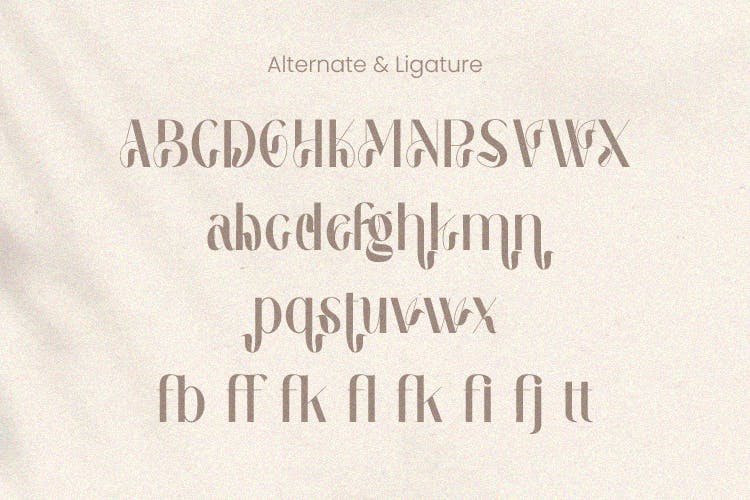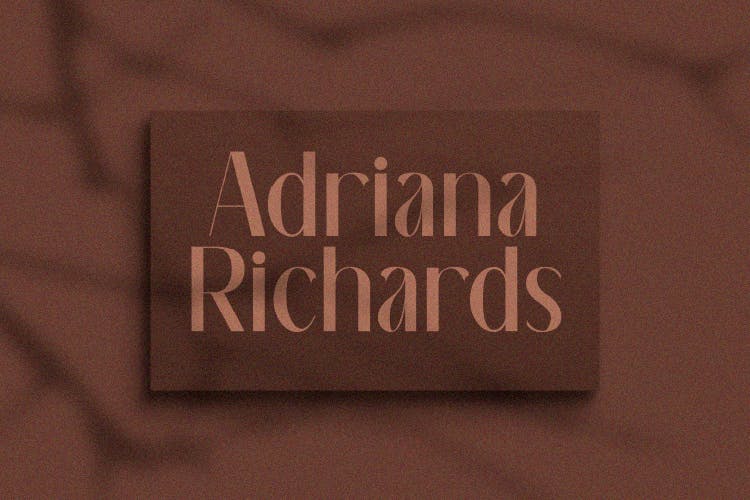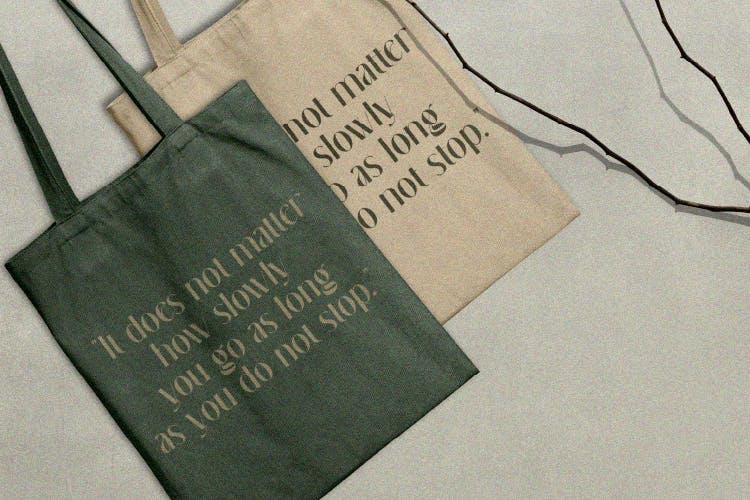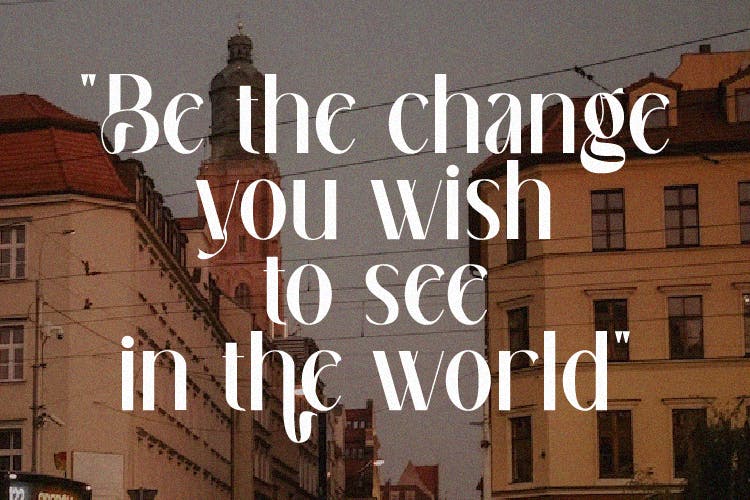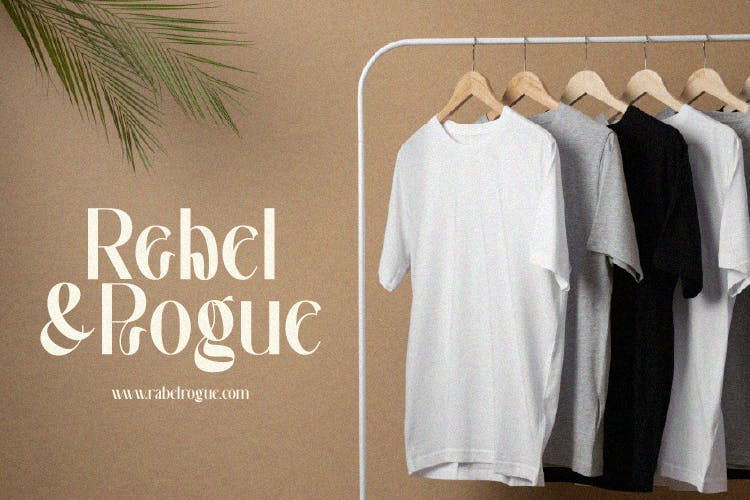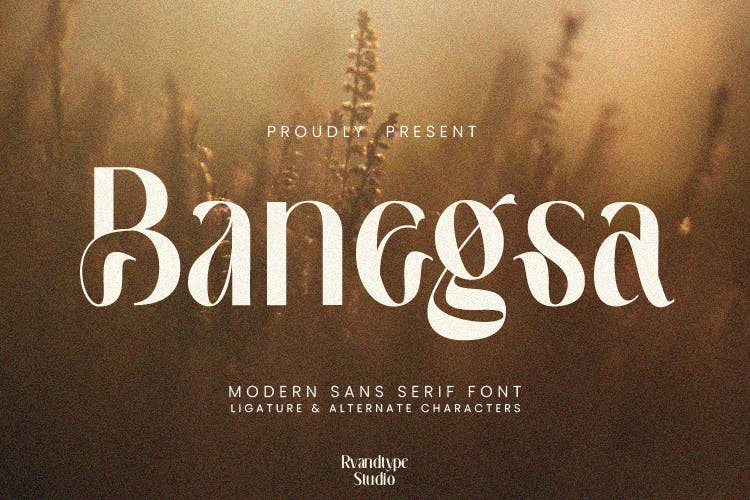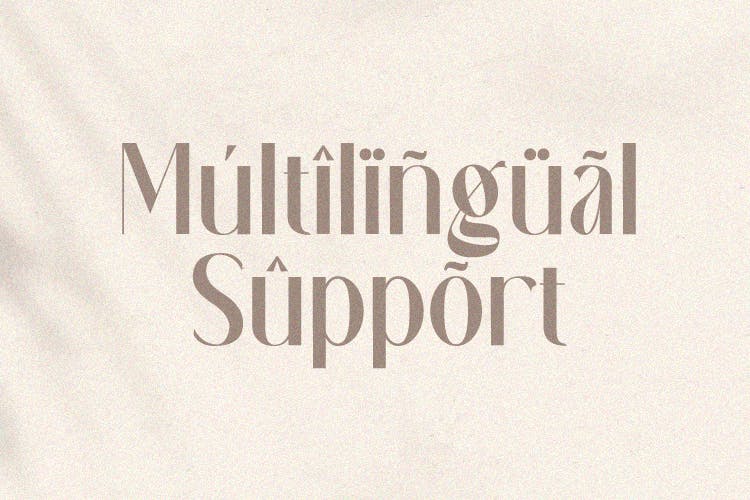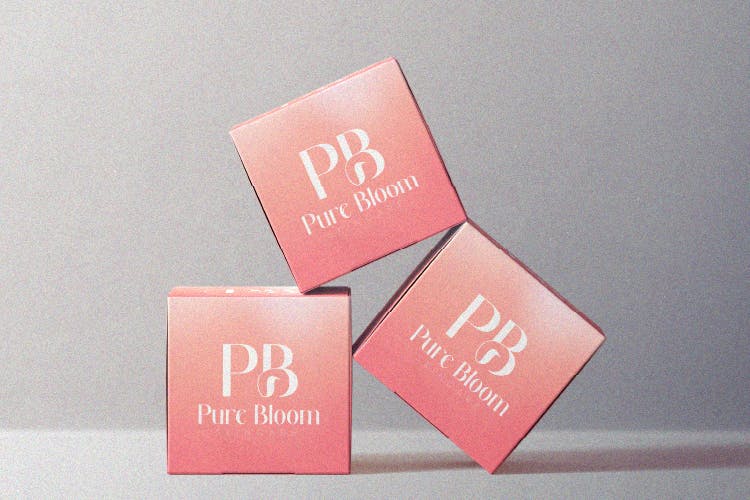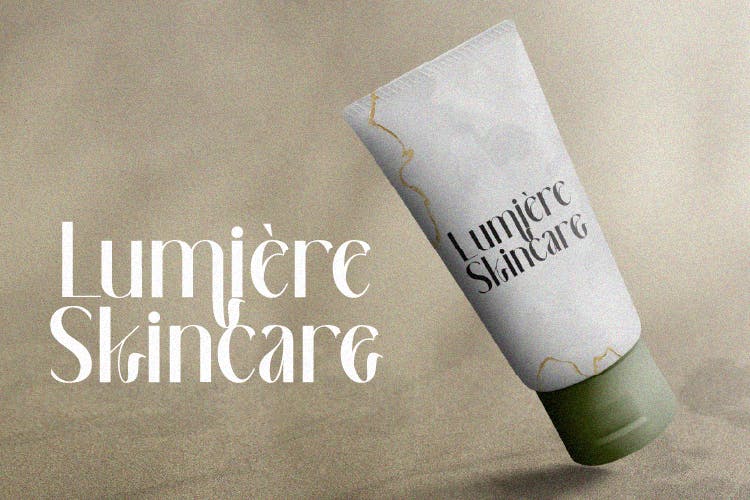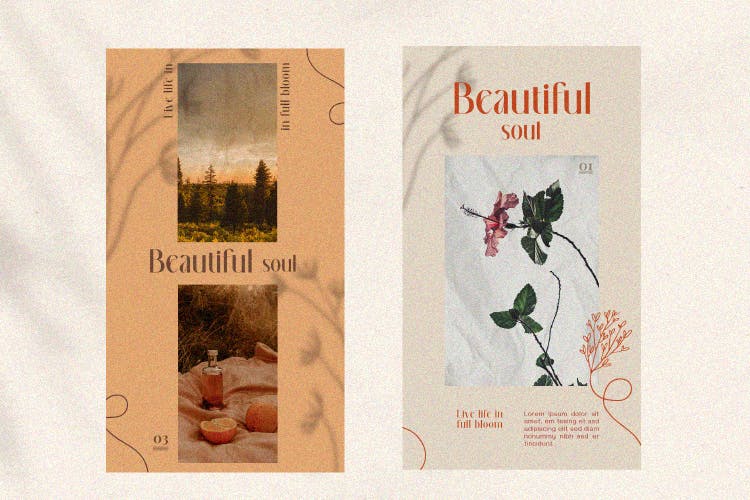
فونت Banegsa یک فونت بدون سری (sans serif) است. طراحی شیک و جذاب آن، این فونت را به انتخابی مناسب برای لوگوها، برندینگ، دعوتنامهها، لوازمالتحریر، طراحیهای عروسی، پستهای شبکههای اجتماعی و بسیاری پروژههای دیگر تبدیل کرده است. فونت Banegsa دارای کدگذاری PUA است که به شما این امکان را میدهد تا به تمامی نمادها دسترسی داشته باشید.